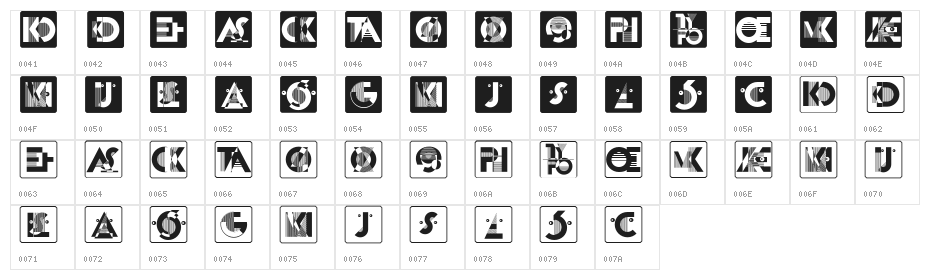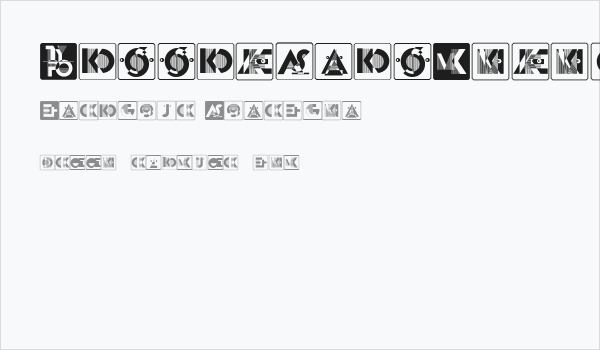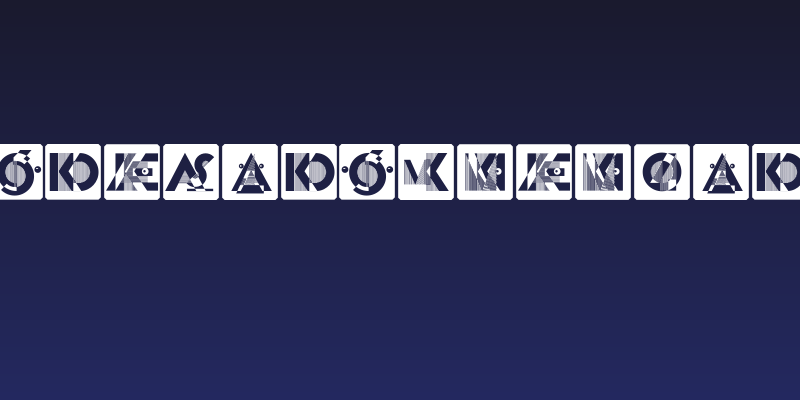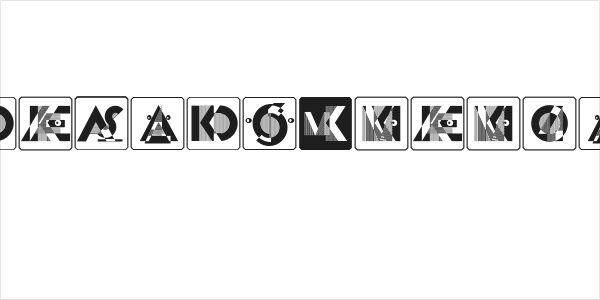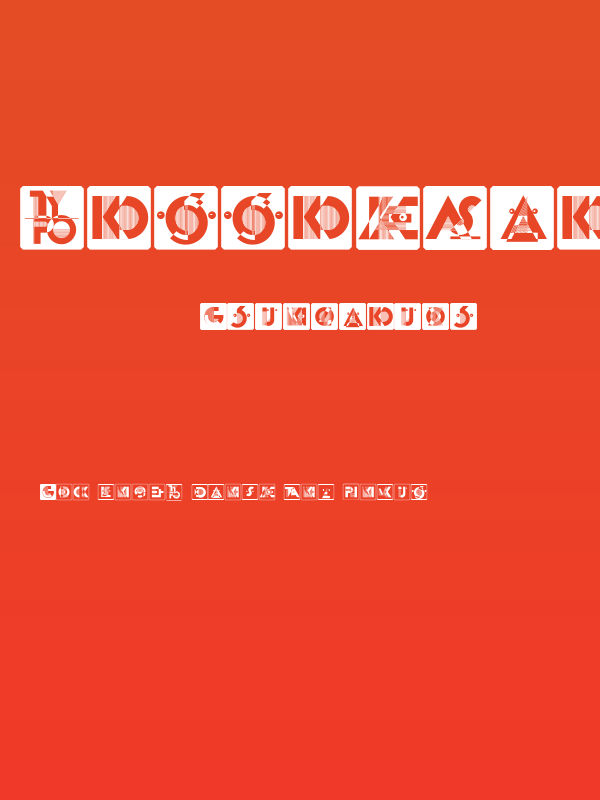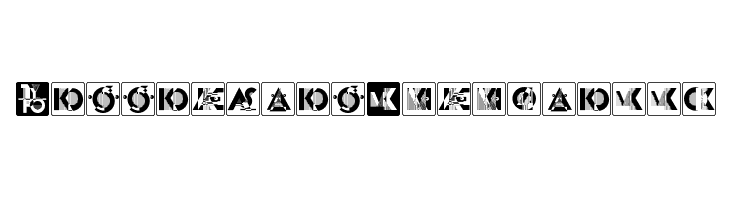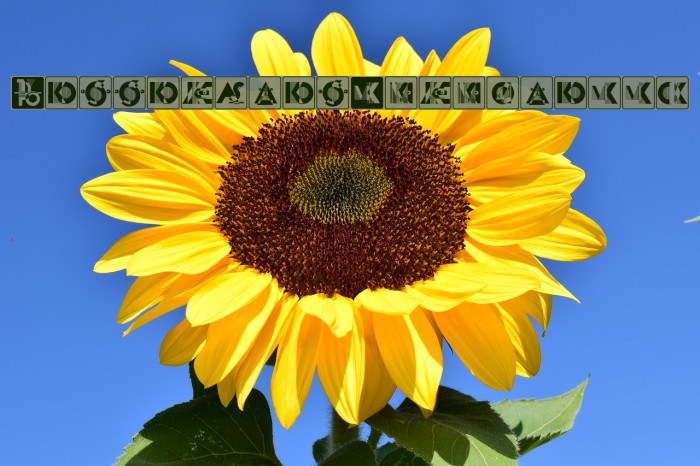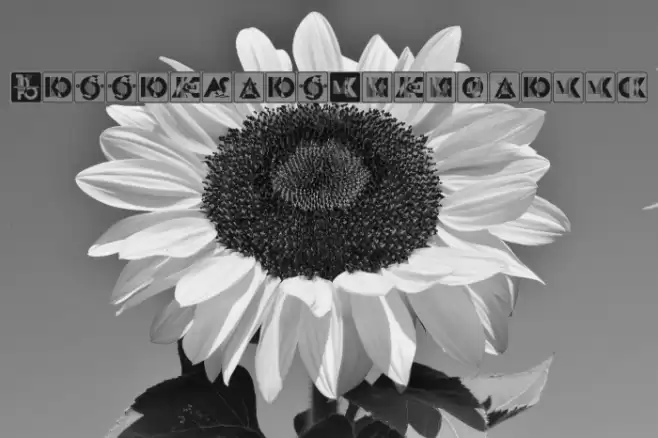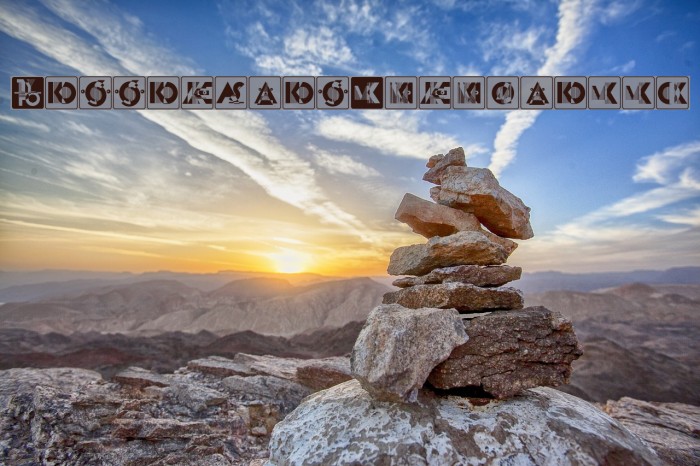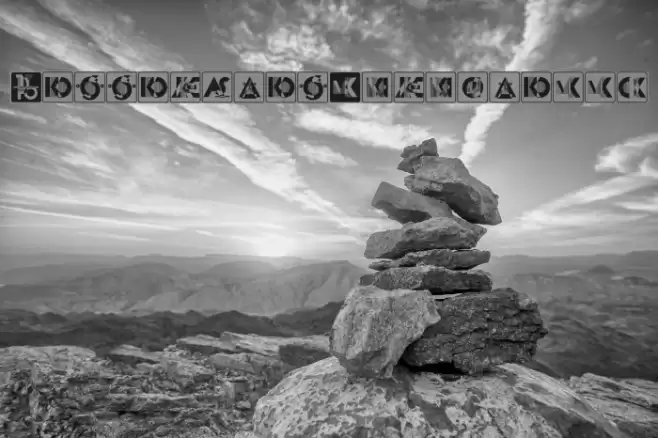
KassandrasMonogramme Font
| Stil general | Modern, Artistic |
| Caz de utilizare | Logos, Headlines, Artistic projects |
| Proiecte propuse | Ideal for branding, logos, invitations, and artistic posters where a unique and striking font is needed. |